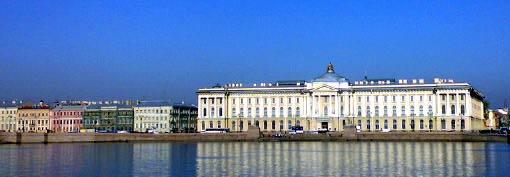
Van woensdag 17 tot zondag 21 september 2008 vond in het prachtige Beloselsky-Belozersky paleis te St. Petersburg de jaarlijkse conferentie plaats van de Association Typographique Internationale (ATypI). Net als in voorgaande jaren was de Dutch Type Library weer sponsor van dit evenement, waar letterontwerpers, fontproducenten, typografen en software-ontwikkelaars vanuit de hele wereld elkaar ontmoetten en lezingen volgden.
Net zoals voor de ATypI conferenties in Lissabon in 2006 en Brighton in 2007 organiseerde de Dutch Type Library ook dit jaar een dtl FontMaster Track als onderdeel van het TypeTech Forum, waarmee traditioneel de eerste twee conferentiedagen worden gevuld. Sprekers waren Dr. Jürgen Willrodt en Peter Rosenfeld van urw++, Hanna Hakala, en Frank E. Blokland van dtl.
Samen met haar Duitse partner urw++ ontwikkelt de Dutch Type Library software voor de professionele fontproductie, zoals dtl FontMaster.
Hoofdprogrammeur Dr. Jürgen Willrodt demonstreerde OTMaster, een uiterst specialistische applicatie voor het bewerken van OpenType fonts, die door dtl en urw++ begin 2009 op de markt wordt gezet.
Peter Rosenfeld, Managing Director van urw++, liet zien dat veel van de actuele fonttechnologie zijn oorsprong vindt in het Ikarus systeem, dat in de jaren zeventig van de vorige eeuw het licht zag en onder andere de basis vormt voor dtl FontMaster.
De Finse letterontwerpster Hanna Hakala werkt momenteel aan een nieuw dtl lettertype. Zij is met name gespecialiseerd in de ontwikkeling van Cyrillische karakters en schrijft in opdracht van de Dutch Type Library een boekje met als titel Comprehensive notes on the Design of Cyrillic Letters, dat begin 2009 moet uitkomen. Bij de Dutch Type Library wordt al geruime tijd gewerkt aan de uitbreiding van alle lettertypen met Cyrillisch en Hanna adviseert daarbij. In St. Petersburg ging zij dieper in op het ontwerpen van Cyrillische lettervormen.
Frank E. Blokland sprak over de automatisering van zowel de fontproductie als van specifieke letterontwerpprocessen en over het combineren van fontproductie-software in workflows.
In het ‘reguliere‘ programma van de ATypI08 conferentie gaf Frank E. Blokland een lezing met als titel Now, then and perception. Hierin stond onze kijk op het verleden centraal en dan met name het beeld dat typografen hebben van historische lettertypen en de factoren die daarbij een rol spelen. Revivals blijken net zoveel een beeld te geven van de tijd waarin ze totstandkwamen als van de oorspronkelijke stijlperioden. Blokland trok daarbij onder meer parallelen met de schilderkunst en liet muziekfragmenten horen.
Januari 2009 kwam de nieuwste module van de fm suite beschikbaar: dtl OTMaster. Het programma wordt ontwikkeld voor Mac os X, Windows en Linux en is bedoeld voor het direct bewerken van OpenType fonts.
De functionaliteit omvat onder meer het toevoegen en bewerken van glyphs, het reviseren van de (naam)tabellen, het checken van de consistentie en het im- en exporteren van OpenType Layout features.
Als letterontwerper (van onder meer dtl Argo en dtl Paradox) heeft Gerard Unger de afgelopen decennia alle mogelijke successen behaald. Zijn lettertypen worden over de gehele wereld toegepast in huisstijlen, kranten, tijdschriften, boeken en bewegwijzeringen. Zo is dtl Argo onder andere de huisletter van de stad Keulen, ’s werelds grootste brouwer InBev, Koninklijke bam Groep en van technologie-gigant Emerson.
Als docent vierde Unger succesen aan de Gerrit Rietveld Academie, is hij gasthoogleraar aan de Universiteit van Reading en sinds 2006 hoogleraar Typografische Vormgeving aan de Universiteit van Leiden. In 1991 ontving hij de Maurits Enschedé-prijs.
In 2008 kwam daar het eredoctoraat van de Universiteit Hasselt bovenop. Zijn promotor, Professor Swinnen, verwoordde het zo:
‘[...] Gerard Unger is een van die zeldzame talenten die de theorievorming van de typografie weet te koppelen aan het ontwerp van innovatieve letters [...]’.